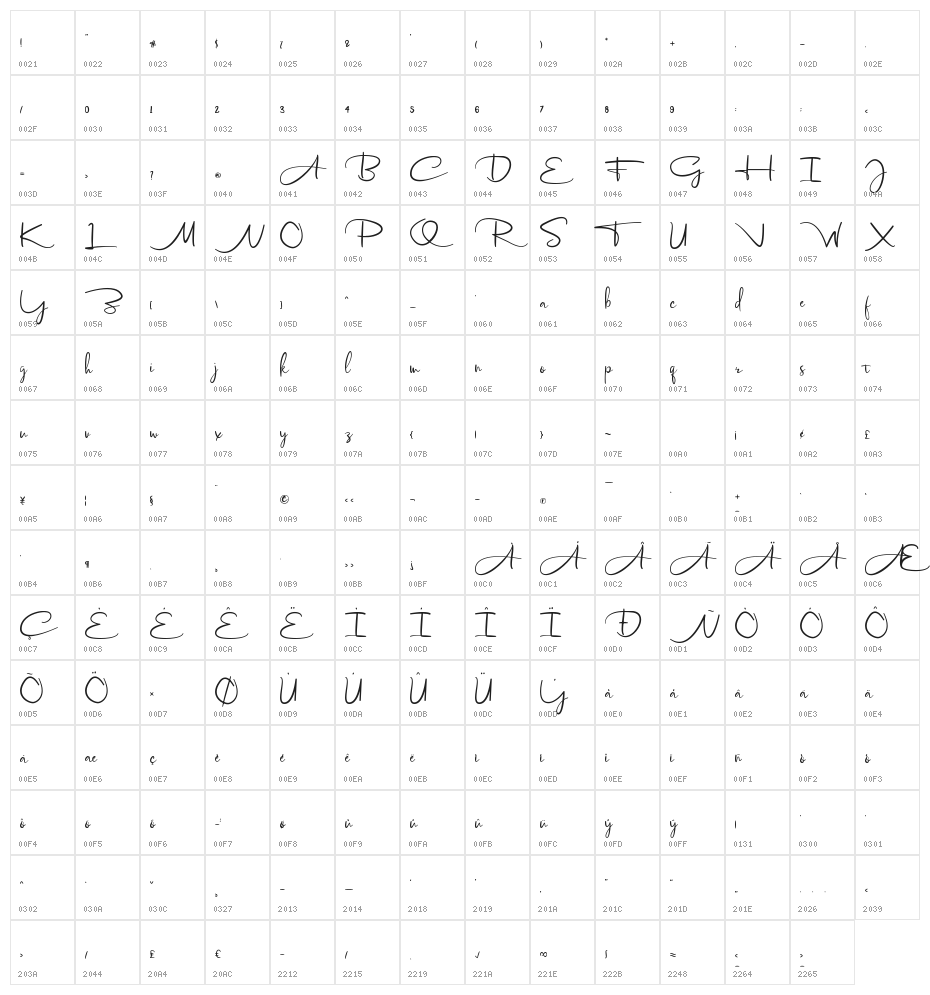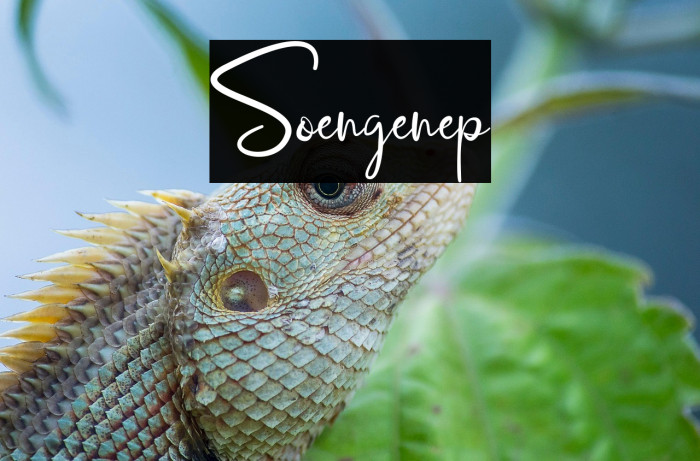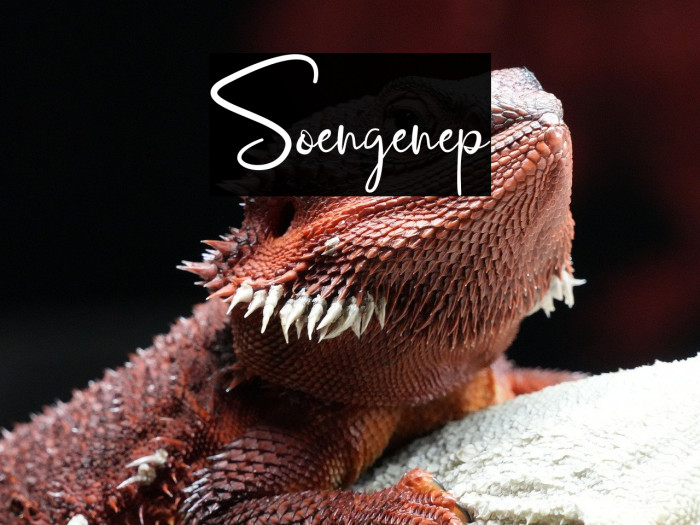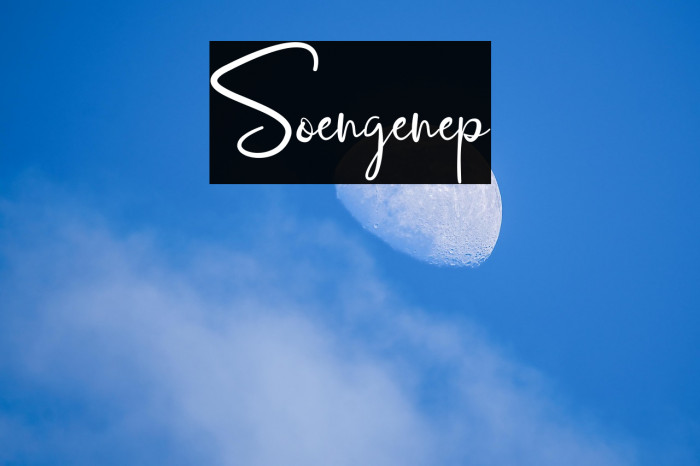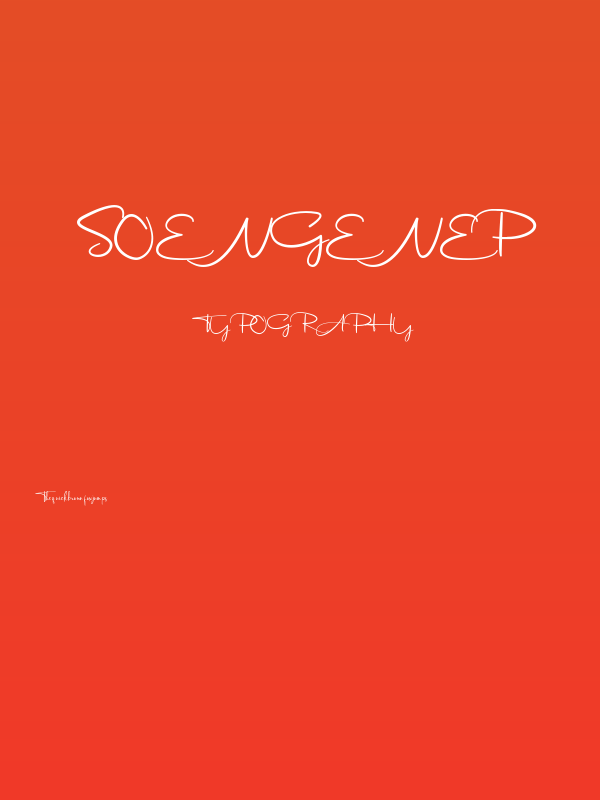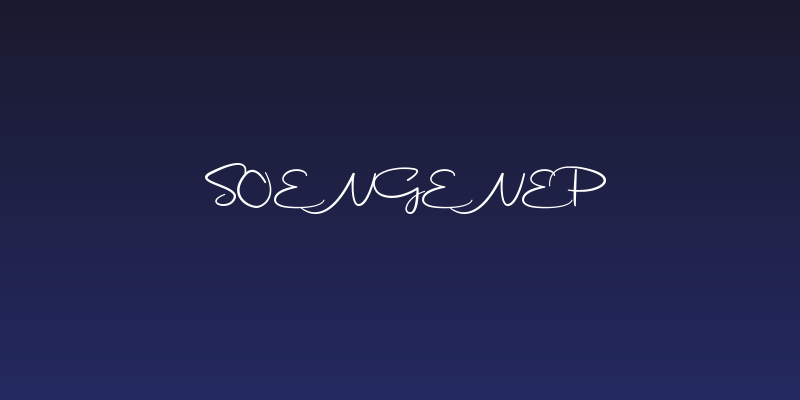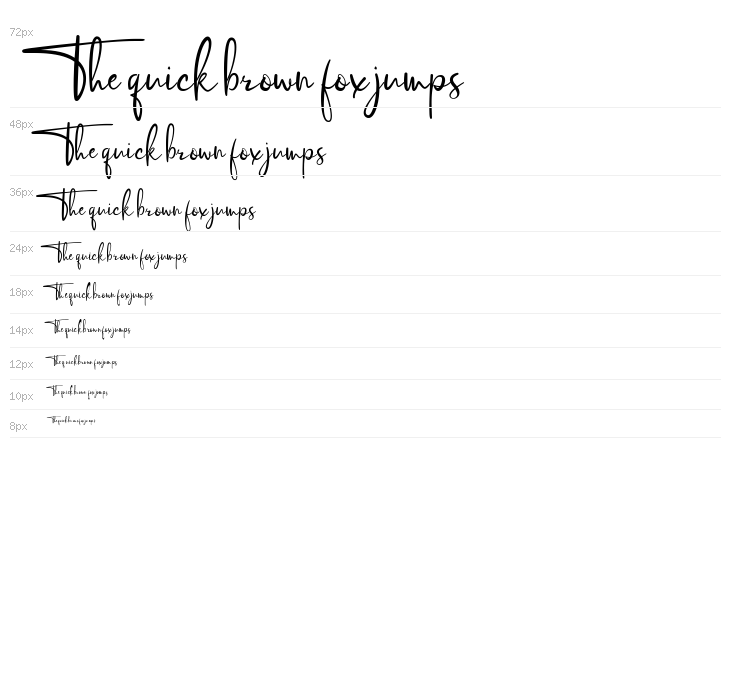
Soengenep Font
| Stile generale | Elegant, Artistic |
| Caso d'uso | Headlines, Invitations, Branding |
| Progetti proposti | Ideal for wedding invitations, greeting cards, personal branding, and artistic projects. |